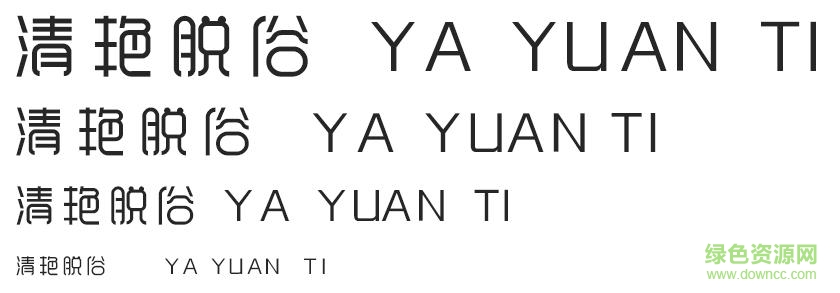
印品雅圓字體
印品雅圓體是一款印刷字體,采用大量的弧線將字體變得生動(dòng)而活潑,變得可愛(ài)有趣,可用于廣告設(shè)計(jì)、海報(bào)標(biāo)題等等方面。歡迎大家來(lái)綠色資源網(wǎng)踴躍下載使用!
印品雅圓體
所謂圓體是英文書(shū)法的延伸及日?;?,較為隨意。雅圓體,對(duì)弧形做了內(nèi)凹外凸的處理,使得筆畫(huà)更加居中圓滑。表面結(jié)構(gòu)勻稱統(tǒng)一,字型做了細(xì)致比例的調(diào)整,整體觀來(lái)更加珠圓玉潤(rùn)。加強(qiáng)裝飾感的同時(shí),多添了一分俏皮可愛(ài)。